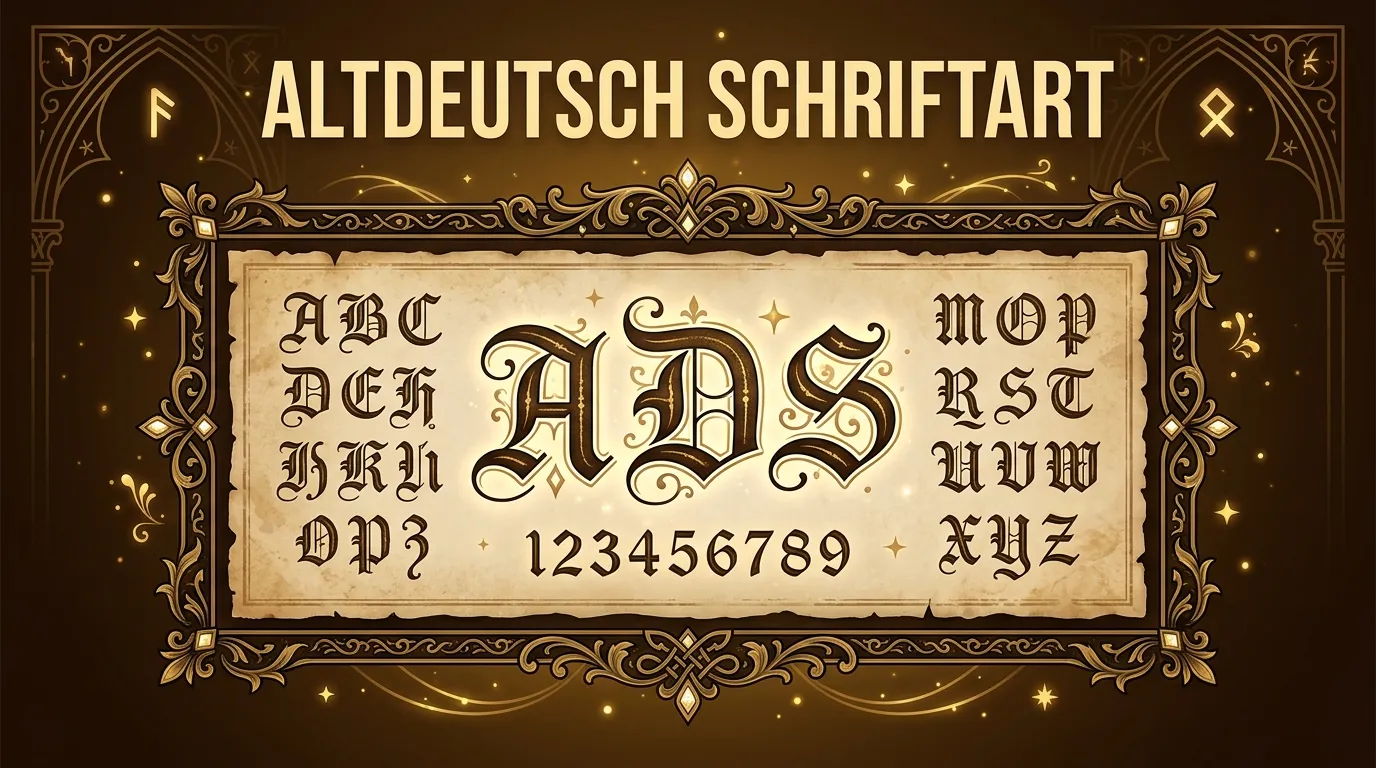
Verwandle deinen Text in historische altdeutsche Schrift: Fraktur, Gotisch und Schwabacher. Für Tattoos, Branding, Social Media und Ahnenforschung. Kostenlos, ohne Anmeldung, direkt im Browser.
Altdeutsche Schrift für Instagram, Tattoos und Branding
Altdeutsche Frakturschrift erlebt ein Comeback: nicht als Alltagsschrift, sondern als dekoratives Stilmittel. Auf Instagram und TikTok nutzen Creator den markanten Stil für Bios und Profilnamen. In der Tattoo-Szene gehört Fraktur/Blackletter zu den beliebtesten Schriftstilen für Namen, Daten und Lebensmottos.
Für traditionelles Handwerk-Branding (Brauereien, Bäckereien, Metzgereien) signalisiert altdeutsche Schrift Tradition, Qualität und regionale Verwurzelung. Wichtig: Für professionelle Logo-Entwürfe und Drucksachen sollten echte OTF/TTF-Schriftarten verwendet werden, die volle Zeichensatzunterstützung bieten.
Eng verwandt mit altdeutscher Schrift ist die Gothic-Schrift für einen internationalen Blackletter-Look , die denselben ästhetischen Ursprung hat, aber international breiter genutzt wird.
Fraktur, Schwabacher, Kurrent, Sütterlin: Was ist was?
Die deutsche Schriftgeschichte umfasst mehrere verwandte, aber unterschiedliche Schriftfamilien. Textura, Schwabacher und Fraktur sind Druckschriften (für den Buchdruck). Kurrent und Sütterlin sind Handschriften (für Brief- und Alltagsschrift). Alle fünf gehören zur Familie der „gebrochenen Schriften": so genannt, weil die Strichführung gebrochen ist, statt in runden Bögen zu fließen.
Die Fraktur dominierte den deutschen Buchdruck von ~1500 bis 1941, als der sogenannte „Normalschrifterlass" die Umstellung auf Antiqua (lateinische Schrift) anordnete. Heute ist Unicode-Fraktur eine moderne Annäherung: sie erfasst den visuellen Charakter, aber nicht alle historischen Details wie Ligaturen (ch, ck, st, sz) oder das lange ſ.